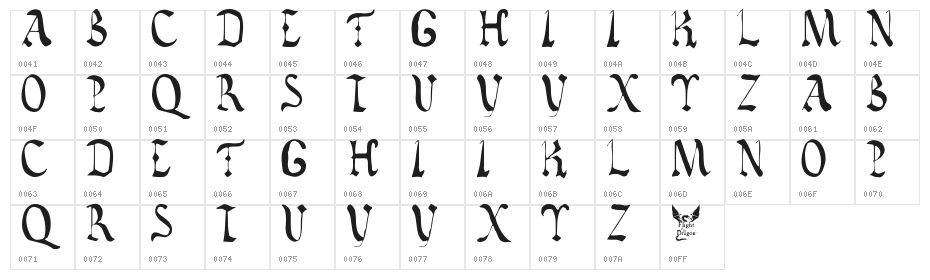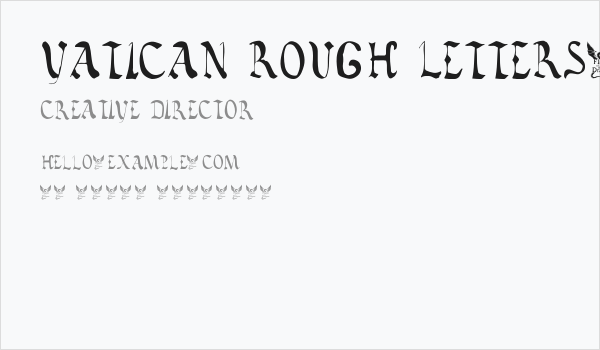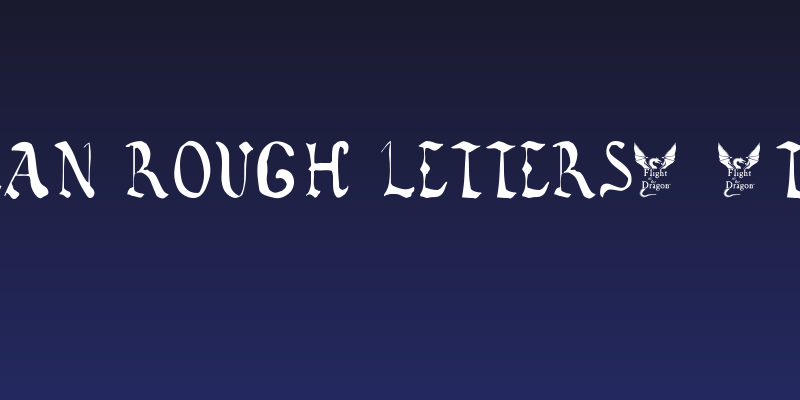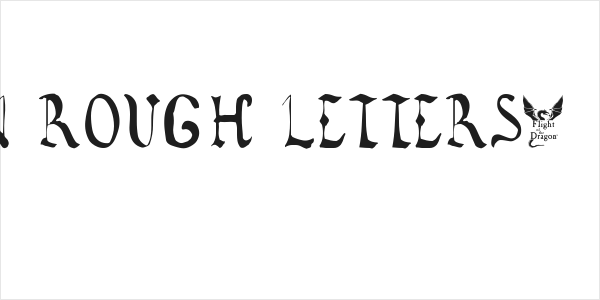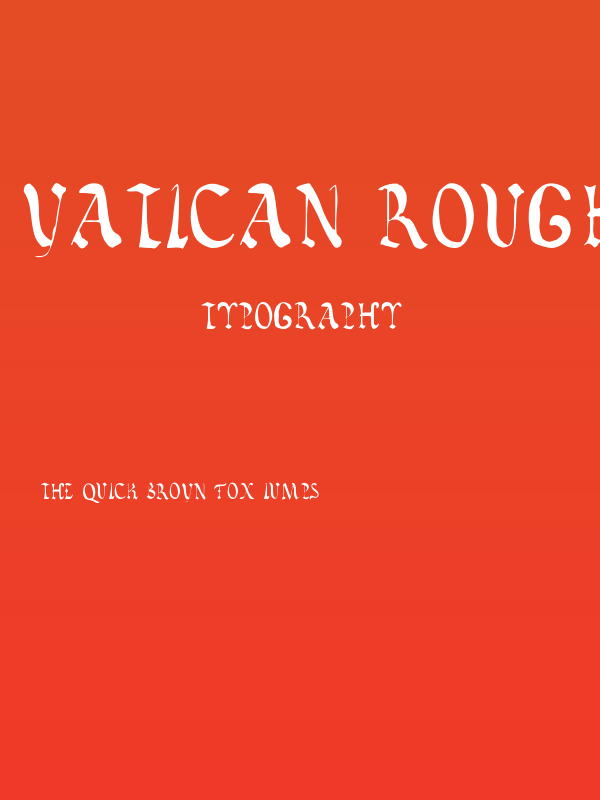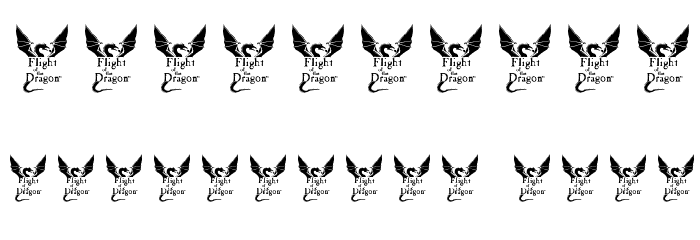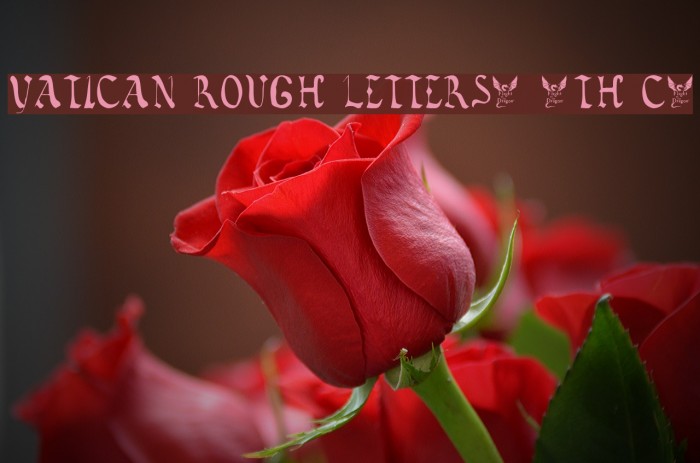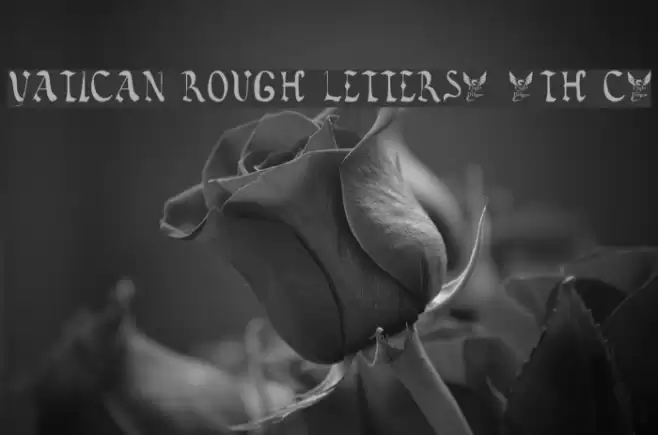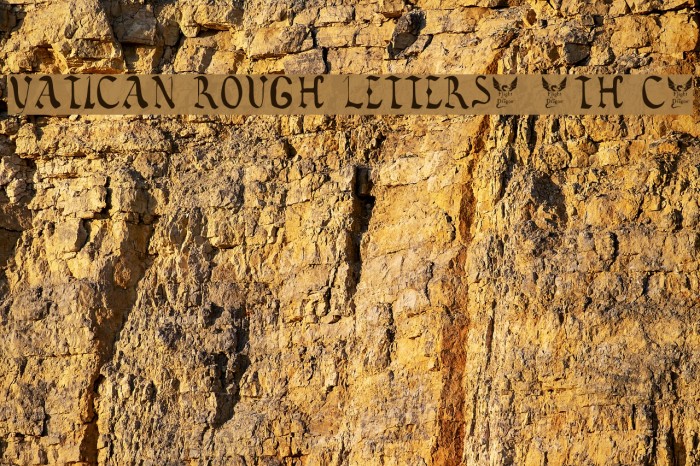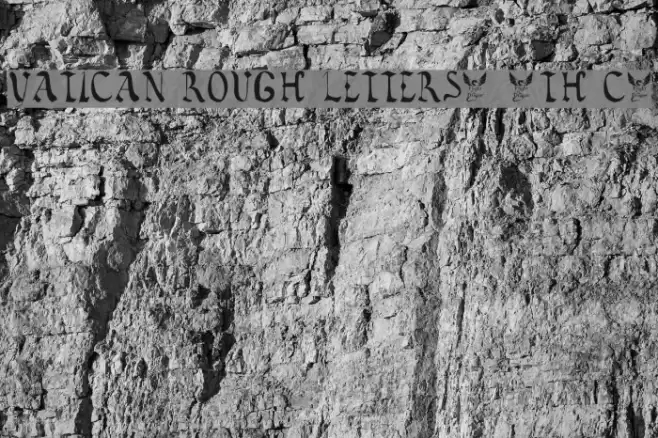
Vatican Rough Letters, 8th c. Font
✎ Script
| Categorías | Script |
| Estilo general | Vintage |
| Proyectos propuestos | Ideal for historical themed designs, book covers, posters, and branding that seeks a vintage or medieval aesthetic. |
Vatican Rough Letters, 8th c.